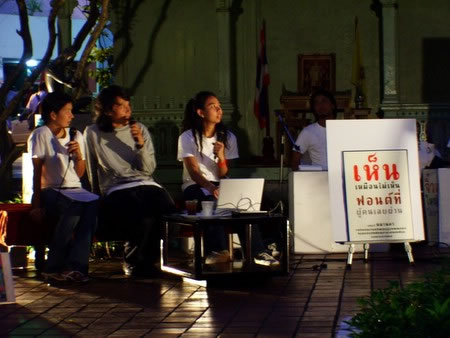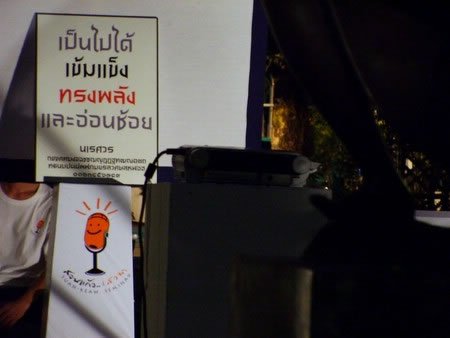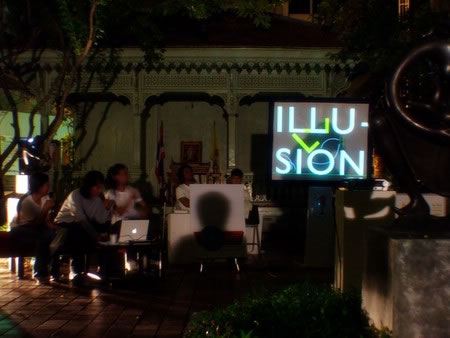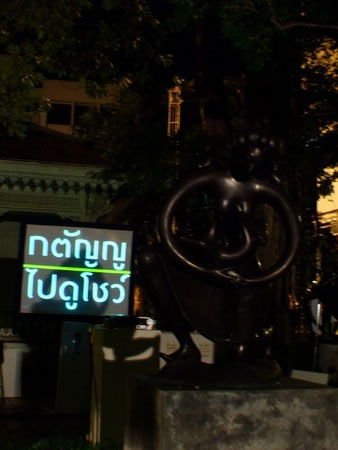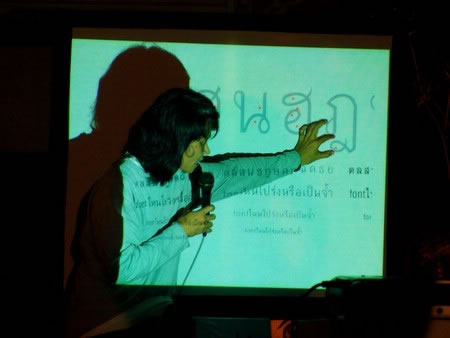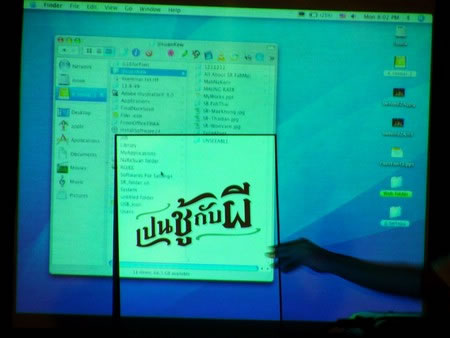
ประมวลภาพเสวนาสวนแก้ว | อ.โรจี้~
สัปดาห์นี้เป็นเรื่องเกี่ยวกับ อ.ไพโรจน์ และผลงานของทั่น
เห็นว่าเกี่ยวกับฟอนต์ ก็เลยไปฟังให้ขำใจ :27:
"เห็นเหมือนไม่เห็น"
แนวคิดของฟอนต์ เอสอาร์ หมานคร ที่เอามาจากป้ายไทยๆ แบบข้างทางนี่เอง
เอสอาร์ นเรศวร
เข้มแข็ง แต่อ่อนช้อย .. เอ๊ะยังไง
เดี๋ยวได้พบกันเร็วๆ นี้ครับ กับภาพยนตร์เรื่องใหม่ของท่านมุ้ย
(จานโรจแกบอกว่ากำลังขัดเกลาอยู่ ตัวนี้ใช้เวลาทำตั้งหกเดือนแน่ะ)
เปิดบรรยายฉบับเดียวกับที่กรมทรัพย์สินทางปัญญาครับ
ว่าด้วยเทคนิคการออกแบบตัวอักษร การลวงตา
ที่เห็นในภาพคือการเอาตัว L มาตะแคงดู จะเห็นว่าความหนาของแกนตั้งกะแกนนอนนี่มันไม่เท่ากันนะจ๊ะ
แต่เราดูเหมือนเท่ากันเพราะเป็นการลวงตาของคนออกแบบไง .. เอ้า จำไว้ใช้ให้หล่อสวยเอย
สังเกตเชิงของ ญ หญิงสิครับ ระยะบรรทัดขนาดนี้ไม่ตีกับโชว์ข้างล่าง
(อ.เสนอไอเดียการออกแบบ ญ หญิงแบบย่นเชิงขึ้นไปรวมในเส้นบรรทัดในยามปกติ อันนี้น่าสนใจดีนะครับ)
อากาศภายในภับภายนอกของตัวอักษรจะต้องออกมากลมกล่อมกัน
สังเกตการเฉลี่ยน้ำหนักในช่องไฟภายในภายนอกของเอสอาร์ ฟ้าใหม่นี่สิจ๊ะ
แบบตัวอักษรจากหนังเรื่องนี้ จานโรจกำลังจะทำมาเป็นฟอนต์ครับ
อีกไม่นานเราคงได้เห็นกัน
จริงๆ ตูก็มีโครงการที่ว่าจะ ว่าจะมาตั้งนานแล้วนะ
เอาป้ายศาลากลางจังหวัดเพชรบุรีมาทำฟ๐นต์
ซึ่งออกมาอารมณ์จคล้ายๆ กันนี้ แต่จะครึ่งๆ กับ PSL Thaicommon หน่อยๆ
ลืมบอกไป ฟอนต์ด้านล่างนั่นคือ เอสอาร์ 50 ปี เดค